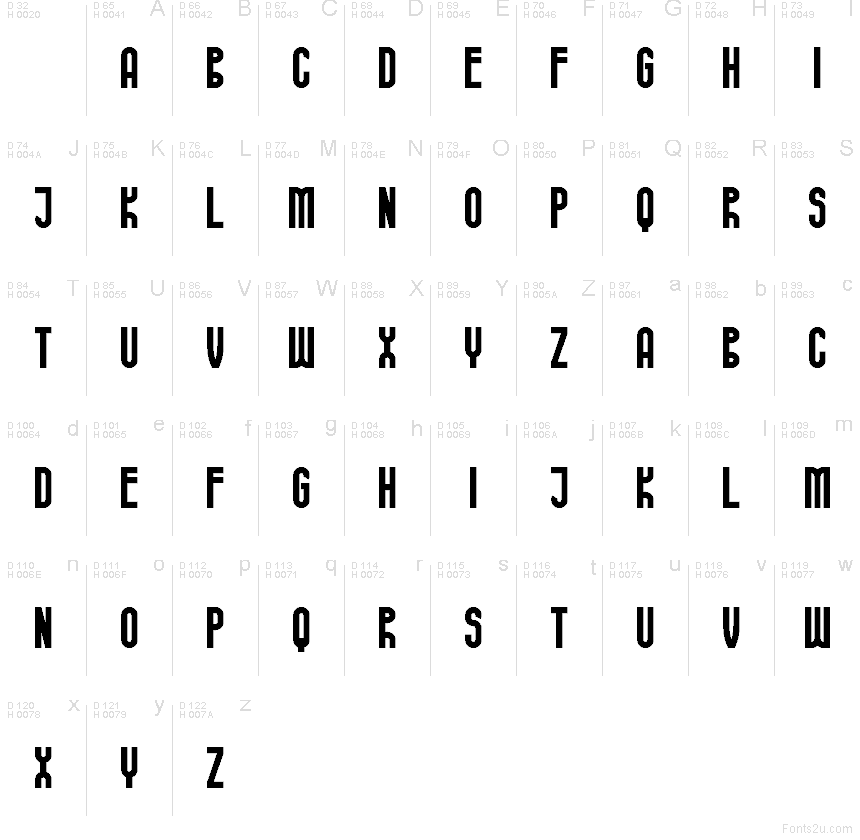
Broadcaster Flat de Vladimir Nikolic es una fuente display de estilo retro gratuita, con letras gruesas y redondeadas que evocan la fluidez de la era de la radiodifusión. Sus mayúsculas parecen construidas con trazos anchos y uniformes, con aperturas ovaladas altas y uniones recortadas que le dan al diseño un ritmo geométrico suave, evitando esa sensación industrial demasiado rígida.
Encaja a la perfección en titulares de pósteres, portadas de discos, bocetos de logotipos, tarjetas de títulos y packaging que buscan una estética setentera sin caer en lo trivial. Al ser gratuita, también es ideal para titulares de portadas y bloques de branding breves; sus curvas gruesas y formas internas estrechas hacen que el texto se vea compacto, contundente y fácil de componer.